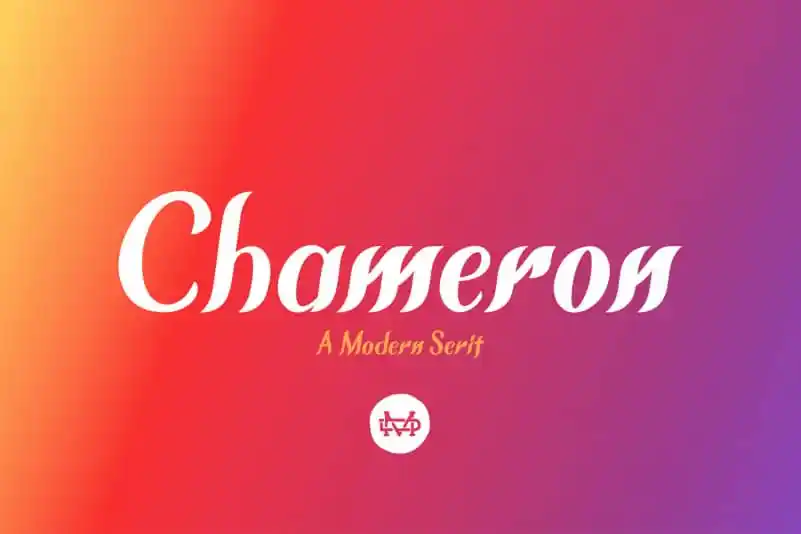
Esta fonte está disponível gratuitamente para uso pessoal, uma vez que qualquer doação é muito apreciada. Se você achar útil ou valiosa, sua contribuição nos ajudará a criar mais fontes como esta. A Chameron Typeface foi criada pelo designer madeDeduk, e é um tipo de sans serif perfeito para diversos tipos de projetos gráficos. Com linhas limpas e leves, essa fonte oferece uma ótima combinação entre estilo moderno e simplicidade. Seja você um designer de branding ou criador de conteúdo digital, a Chameron pode se adaptar perfeitamente às suas necessidades. Não hesite em doar para apoiar o desenvolvimento de mais títulos úteis como este!